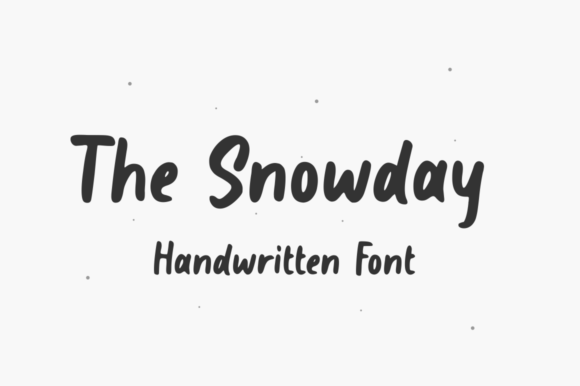
Snowday - это простой и милый матовый рукописный шрифт.
У него красивые и хорошо сбалансированные символы, и поэтому он подходит для широкого спектра дизайнов.
Добавьте его к своим самым креативным идеям и заметите, как они оживут!